Một trong những yếu tố quan trọng không thể thiếu trong thiết kế là font chữ, nó có thể tạo nên sự thành công hoặc phá vỡ thiết kế của một logo. Việc lựa chọn font chữ thích hợp có thể làm tăng sự tác động của logo tới thương hiệu của bạn, và ngược lại, lựa chọn font chữ không phù hợp sẽ làm mất tính thẩm mỹ, truyền đạt sai thông điệp mà bạn và thương hiệu muốn truyền tải.
1. Garamond.
“Kiểu chữ vượt thời gian” Garamond đã được Claude Garamond và Jean Jannon sáng tạo ra từ nhiều thế kỷ trước, là font chữ Serif chứa đầy sức biểu cảm do vậy bạn có thể sử dụng nó để thể hiện sự vui tươi. Logo của American Eagle cũng đã sử dụng phông chữ này một cách đơn giản mà rất hài hòa.
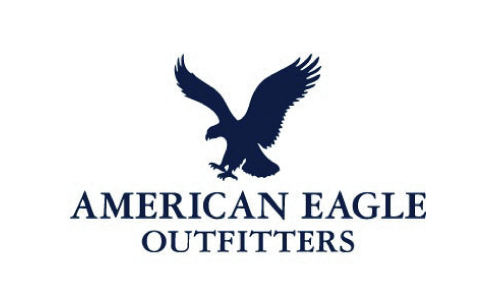
2. Brandon Grotesque
Font Brandon Grotesque là một sans-serif khác biệt bởi chiều cao thấp, tuy nhiên chính nét độc đáo này lại giúp nó có độ chắc chắn nhất định. Đây cũng chính là câu trả lời cho sự phổ biến của nó với các thiết kế hiện đại. Font chữ độc đáo này được sử dụng trong logo Comedy Central.
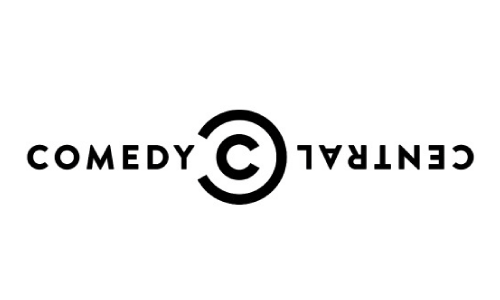
3. Proxima Nova
Sự cân bằng tỷ lệ giữa sự hiện đại và cổ điển được thể hiện một cách tuyệt đối trên font chữ Proxima Nova. Khi thương hiệu có tính chất kết nối với các phương tiện truyền thông xã hội thì font chữ này là một sự lựa chọn vô cùng đúng đắn, giống như Spotify và Twitter đã sử dụng.
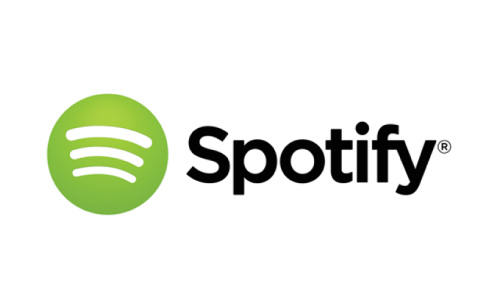
4. Neo Sans
Nét đặc sắc khi sử dụng kiểu chữ Sans-serif với các góc cong khiến cho cường độ font chữ của Neo Sans giảm đi, do đó mang lại cảm giác thân thiện, thoải mái, gần gũi và dễ chịu cho người nhìn. Intel đã tạo ra một thiết kế logo vô cùng chuyên nghiệp với font chữ này.
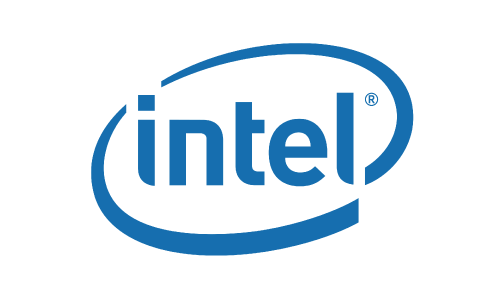
5. Horizon
Horizon là font chữ được các thương hiệu khoa học viễn tưởng ưa chuộng , do ở nó có những góc sắc nét và khiến cho người xem có cảm giác nhìn về không gian. Series “Star Trek” hay bộ phim “ Star Trek: Into Darkness” cũng không ngoại lệ khi lựa chọn sử dụng font chữ này
6. FF Meta
FF Meta tuy được gọi là “Helvetica of the 90s” nhưng điểm khác biệt của hai font chữ này là ở chỗ, Helvetica mang chút cứng nhắc còn FF Meta lại cong và mềm mại hơn. Khi nhìn font chữ này, bạn có thể cảm nhận được nhịp điệu từ những đường cong của nó. Logo của Herman Miller và Weather Channel đều lựa chọn font chữ thú vị này.
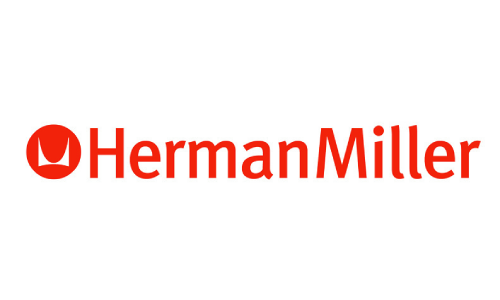
7. Frutiger
Font chữ Frutiger mang tính ứng dụng cao bởi tính năng vượt trội là giúp người đọc có thể đọc rõ dù ở kích thước chữ nhỏ hay lớn. Từ năm 1985, hộ chiếu Thụy Sĩ đã lấy font chữ này làm font chữ chủ đạo của mình,
8. Helvetica.
Helvetica là kiểu chữ vô cùng đơn giản và tiện dụng, do vậy nó được sử dụng rất rộng rãi. Thêm vào đó, việc mang lại cảm giác quen thuộc cho người nhìn, kể cả đó là những nhà quan sát thiết kế chuyên nghiệp, cũng là một điểm cộng lớn cho Helvetica. Chính vì những lí do đó, từ những năm 70 – 80, Xerox, Adobe và Apple đã ưa thích lựa chọn font chữ này.
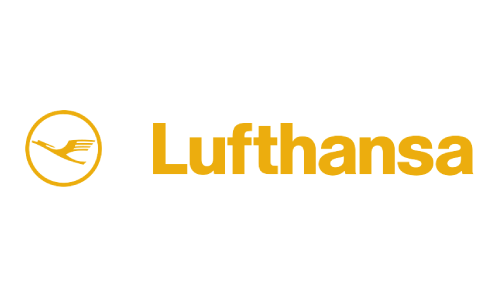
9. Univers
Univers là font chữ rất có sức hút quốc tế và sự tiện dụng đáng kể. Nét đặc sắc của nó đươc thể hiện qua sự cân bằng hình ảnh giữa nét dày và nét mỏng, hình tượng hóa được từng con chữ. Ví dụ điển hình của việc sử dụng Univers trong thiết kế logo đó là logo của eBay.
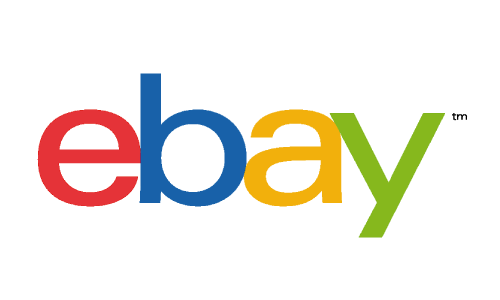
10. Futura
Nếu bạn là một thương hiệu quốc tế với tính cách độc đáo, đang tìm kiếm sự mới mẻ thì Futura chính là gợi ý hoàn hảo cho bạn, bởi ở nó chứa đựng sự cổ điển khác biệt thông qua các mẫu chữ hình học mạnh mẽ. Font chữ này là font chữ được sử dụng nhiều nhất và thành công nhất với các thương hiệu tiêu biểu như FedEX và Swissair.
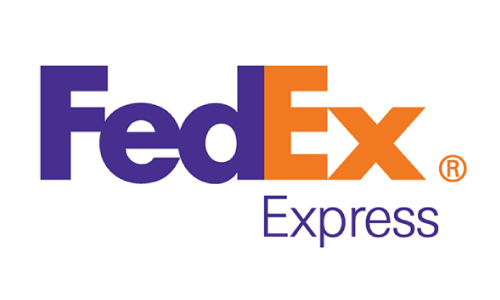
11. Didot
Là một font chữ được ngành thời trang rất ưa chuộng, Didot mang đến cho logo của bạn sự sang trọng, lịch thiệp mà vẫn thanh mảnh, mềm mại, đặc biệt là khi kết hợp với các màu sắc có độ tương phản cao.
12. Bodoni
Thương hiệu thời trang nổi tiếng Calvin Klein đã lựa chọn font Bodoni cho logo của mình bởi lẽ ở Bodoni có sự đối lập nhưng lại gắn kết giữa độ mỏng và dày của chữ. Nhiều năm qua, font chữ này vẫn luôn giữ vị trí ưu tiên cho thiết kế logo của các thương hiệu thời trang khác nhau.
13. Verdana
Verdana cũng là một font chữ có tính hữu ích cao và được các designer sử dụng rất nhiều, rộng rãi. Một điển hình cho sự sáng tạo mới mẻ font chữ này là logo PayPal, họ đã mang đến sự gần gũi, thân thiện, hiện đại mà không kém phần gợi cảm cho người nhìn bằng cách làm tròn các cạnh của chữ cái.
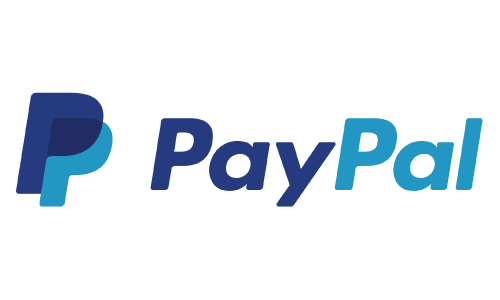
Tất nhiên, thực tế luôn không có quy định cụ thể nào nói rằng bạn không được hay bắt buộc phải sử dụng font chữ nào cho thiết kế logo của mình, bởi đôi khi một font chữ đã cũ với một chút sáng tạo nhỏ sẽ mang đến sự khác biệt đặc trưng của thương hiệu. Chính sự khác biệt đó là chìa khóa giúp bạn thành công trong việc thiết kế logo. Hãy cứ sáng tạo nhiều hơn nhé!